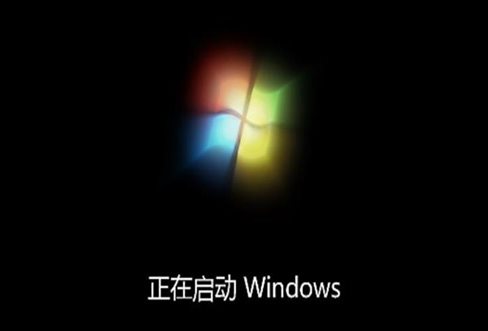
你不知道的“微软雅黑”:真正一字千金
微软雅黑是Microsoft为中文汉字推出的一种字体,和Windows Vista操作系统同期发布,目前广泛地被内嵌在各种网页和软件中。
在Windows系统下微软雅黑文件名为MSYHBD.TTF,这种字体每个字造价在100美元左右,想想新华字典,你就知道什么叫做一字千金了。
你可曾注意过Win7的启动界面,“启”字低人一等
在了解微软雅黑之前,我们需要科普两个关键性名词——ClearType和Hinting。这两个名词是成就微软雅黑的关键技术,但也给微软雅黑的字形带来不少非议。其中包含非常复杂的技术原理,我在这里就用最简单的方式来给大家讲讲。
ClearType技术是Windows系统中的荧幕字体平滑工具,把字体分成红绿蓝(RGB)这三种颜色来搭配显示,能够改善屏幕显示上的文本显示效果(打印出来是没有区别的)。
经过放大的ClearType渲染字体
传统未经ClearType渲染的非黑即白点阵字体(例如常见的宋体),字形看起来笔画分明。
而经过ClearType的字体(例如微软雅黑)边缘是用RGB红绿蓝三种颜色组成。不过在实际大小的文字阅读,边缘看起来没有上图这么明显。上图只是为了更直观看出来区别,对五号的“微软雅黑”进行了放大处理。
未经ClearType渲染的小号字体笔画相连,12%下的“微”字笔画模糊
经过ClearType渲染的字体,整体显示起来更加清晰圆滑,尤其是在小号字体表现更好。而没有经过ClearType渲染的字体,会显得笔画粘连、粗细不均。如果文字篇幅比较长的话,这些突兀黑线条就更加显得与全文格格不入。
不过并不是所有字体都支持ClearType渲染的,只有进行hinting(微调)的字体才能使用ClearType技术。微软雅黑就是经过hinting处理的字体,而hinting是需要人工目视对每个字进行调试的,相比自动化成本要高非常多,所以微软雅黑字体才需要每字造价100美元。
宋体和微软雅黑都是网页所用的安全字体,但现在更多网站都更愿意使用经过ClearType渲染的微软雅黑(像XP这种没有自带雅黑字体的系统打开有该字体的网页,字体就会用被默认的宋体所取代)。而宋体那非黑即白的点阵原理,让宋体看起来比较黑实锐利。加上本身的字高和间距的影响,宋体的屏显效果比微软雅黑差的太多了。
另外微软雅黑体为了让字体看起来更舒适,一直不断地修复改版。现在的windows10上这种字体也得到微软的认可,将操作系统界面UI的字体和微软雅黑进行合并同步,看起来整体界面和样式都更加统一,字形也漂亮了不少。
Win7和Win10下的微软雅黑数字对比
在最新微软雅黑6.20版本中,数字“1”的脚被取消、“7”开始变弯、“8”字也不像以前是用“0”扭出来的,像这样微小的改动数不胜数,文字笔画逐渐和书写体靠拢,字形变得更加简洁方正。
那既然微软雅黑字体优点不少,为什么网上评价却那么差呢?
问题主要可以归分成字体Bug、字体变形和字体美感三个方面。作为一个和Windows Vista同时期的产物,微软雅黑到出生到现在已有十年时间,但在源远流长的中华文字面前,仍然有些不够完善。
微软雅黑的字体Bug:设计师的苦难
虽然微软一直在完善微软雅黑,但其实还是有些遗漏的。在Windows7和早前的Windows8操作系统(Windows10已得到修复)中,微软雅黑中有些字的vmtx(定义每个字高和宽)出现了问题。正常来说,每个字都会有身高和体宽,但“慧”字在微软雅黑中就是个没有“身高”东西。
Windows7系统下微软雅黑的叠字Bug
如果你使用Photoshop,用微软雅黑粗体写下包含“慧”字的句子,在旋转文字方向后就会出现叠字。因为这个字的vmtx中没有给定义字高,所以竖方向的间距为0,字体就会出现重叠。
像这样出现Bug的字还不在少数,像憩、戚、扛、押、拙、拭等都有这个问题,即使手动加空格文字效果也不会等距。如果还在使用Windows7操作系统的朋友,可以自行感受一下设计师的忧伤。
Hinting后字体变形,影响美感。
因为ClearType渲染和Hinting的手工微调,会造成字体的参差不齐,有高有低。严格的讲这并不是字体存在的Bug,高低不一也是需要和有落差的字对比才能够发现。
在Mac、Linux以及windows XP这类没有自带微软雅黑字体的操作系统下,字体就会被自动替换成本机的安全字体,所以下面以图片方式展示。
windows10系统下经过放大的小四字号微软雅黑
比如“言语亲昵”这四个字,首字上浮末尾下沉就非常明显能够看得出来了。还有文章开头提到的Windows7开机的正在启动“启”字下沉,也就是这样的原因。
所以说ClearType和Hinting成就了微软雅黑,但附带的问题也是很多用户嫌弃它的理由。虽然微软雅黑长得方正、字形统一,但从没有“字体等高”一说。
字体也有大学问,虽然字体本身就是平淡无味的东西,但一个好的字体能提高阅读的质量。
微软雅黑作为首款全面支持ClearType屏显技术的简体汉字,看似简单却值得深究。
至于美感这回事就见仁见智了,喜欢就用不喜欢就别用,反正作为Winboy我看着是挺舒服的。